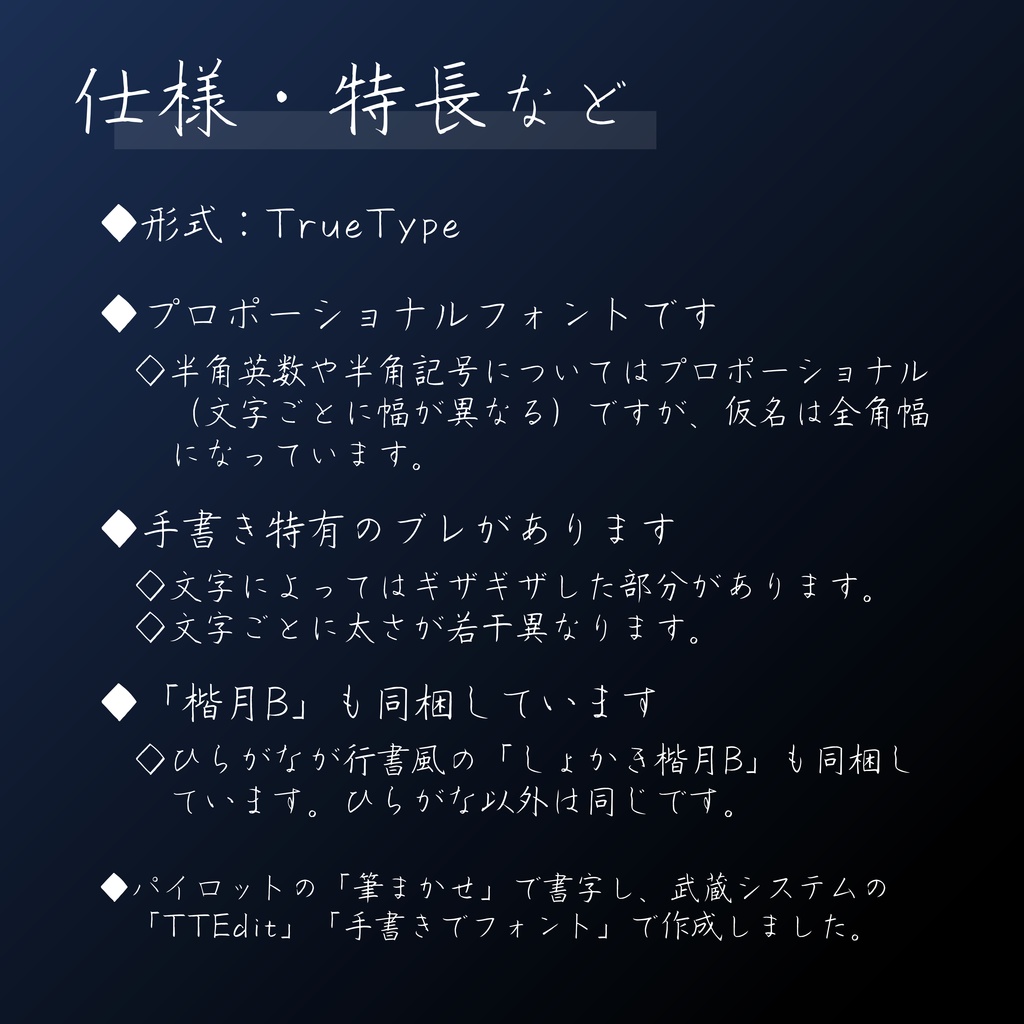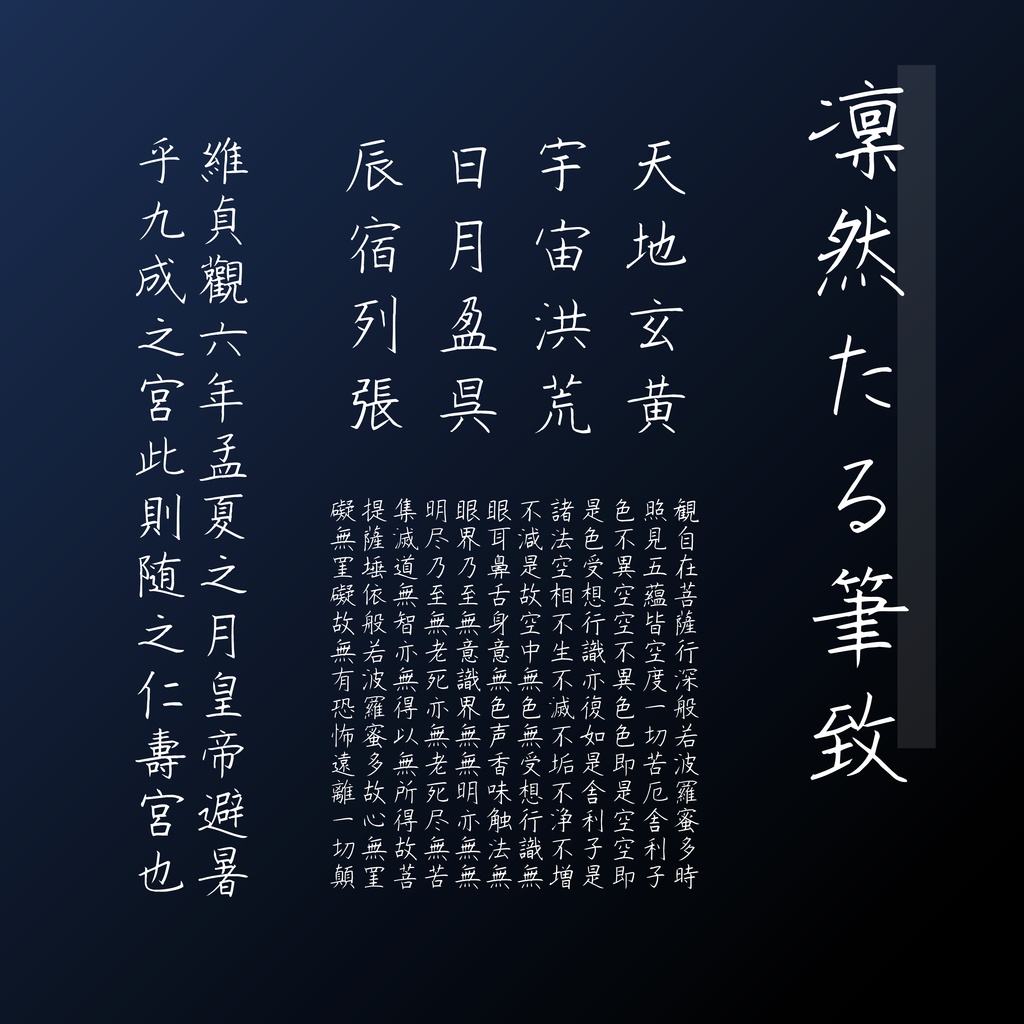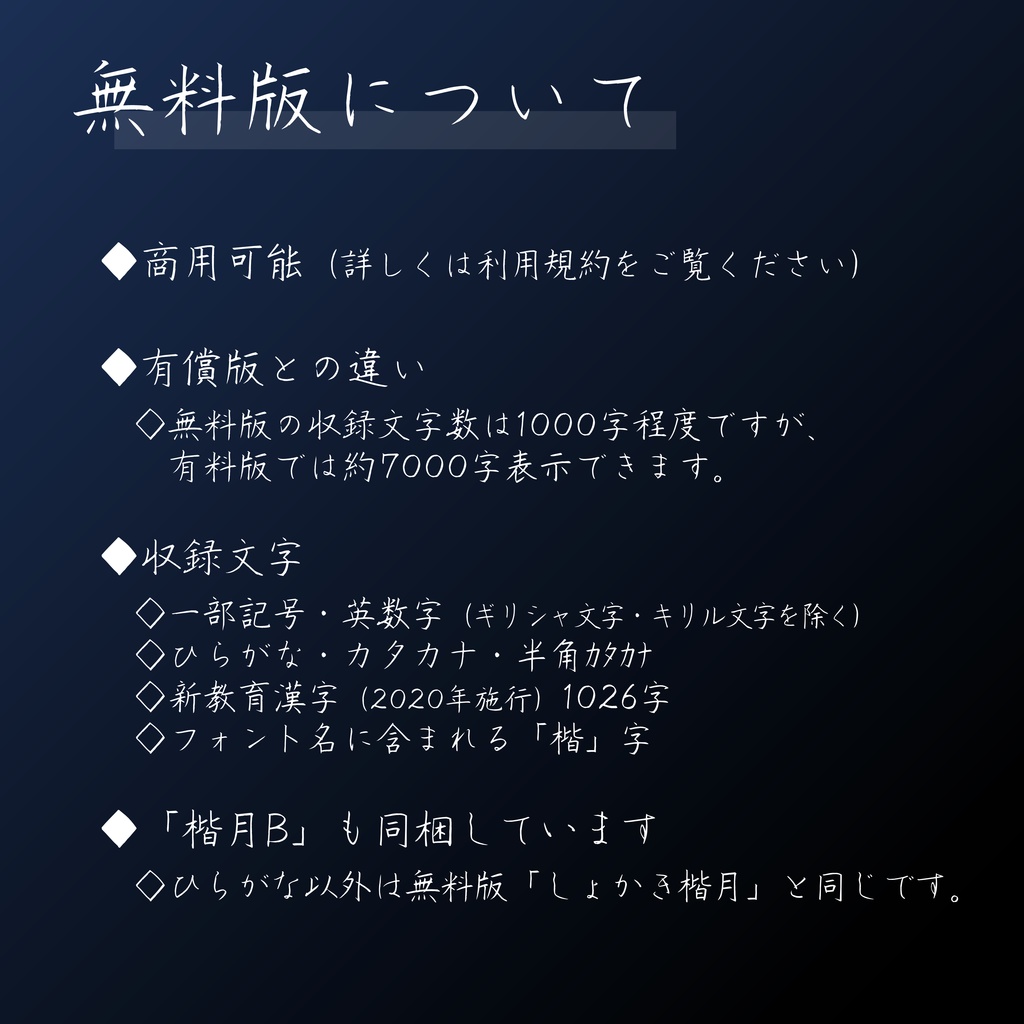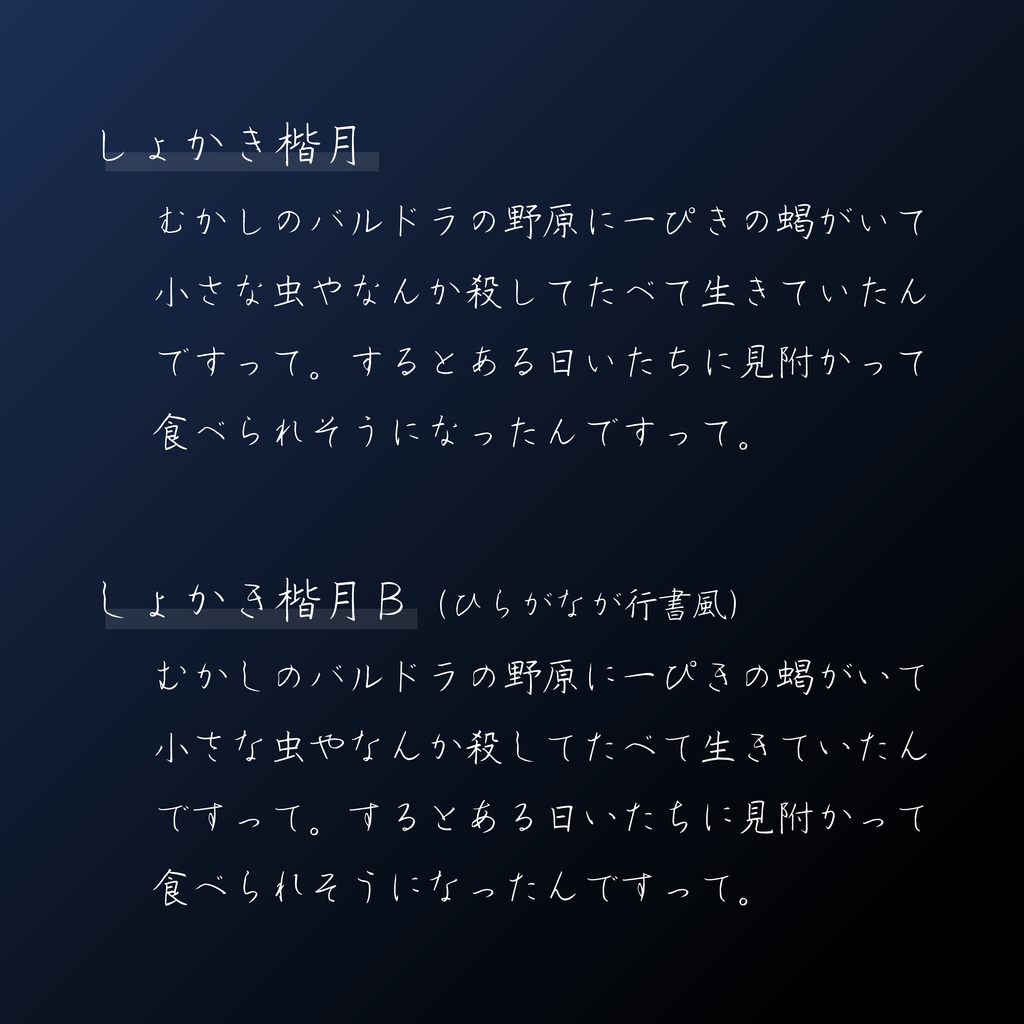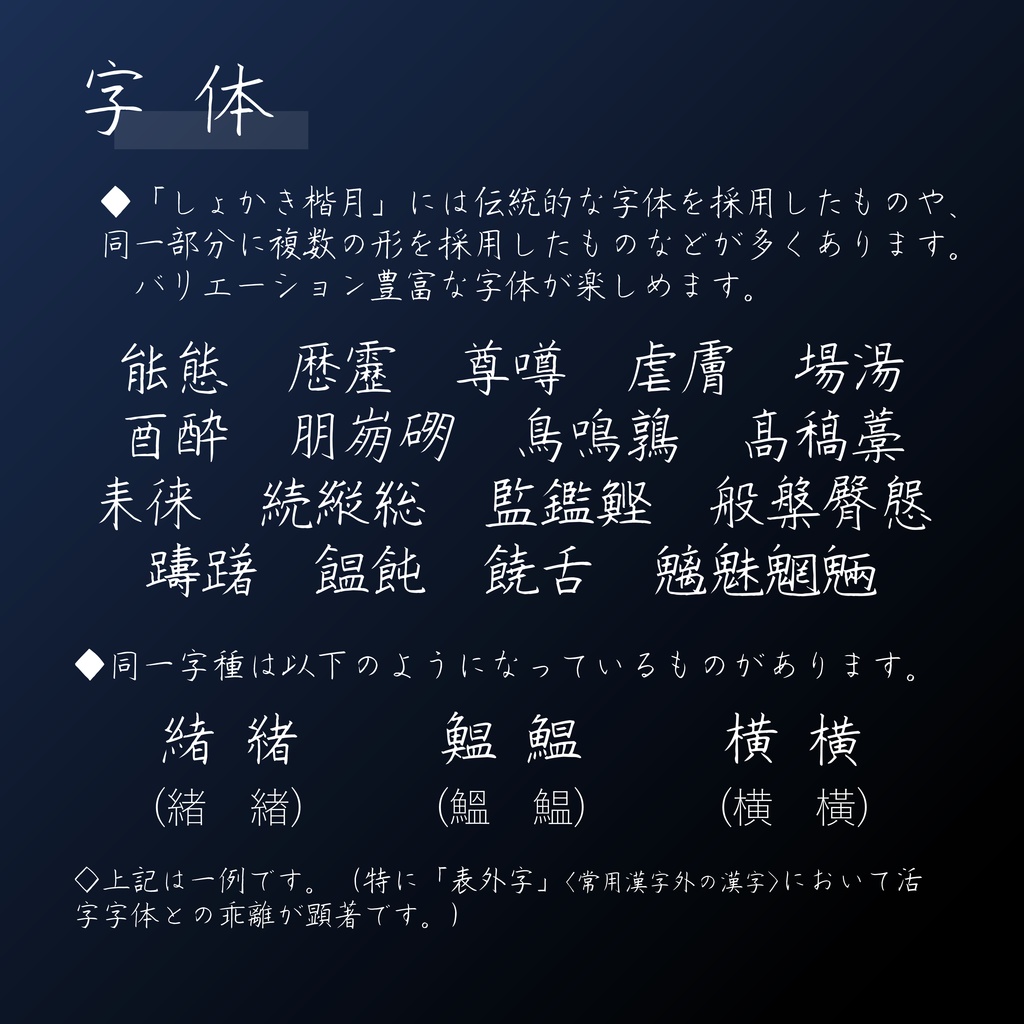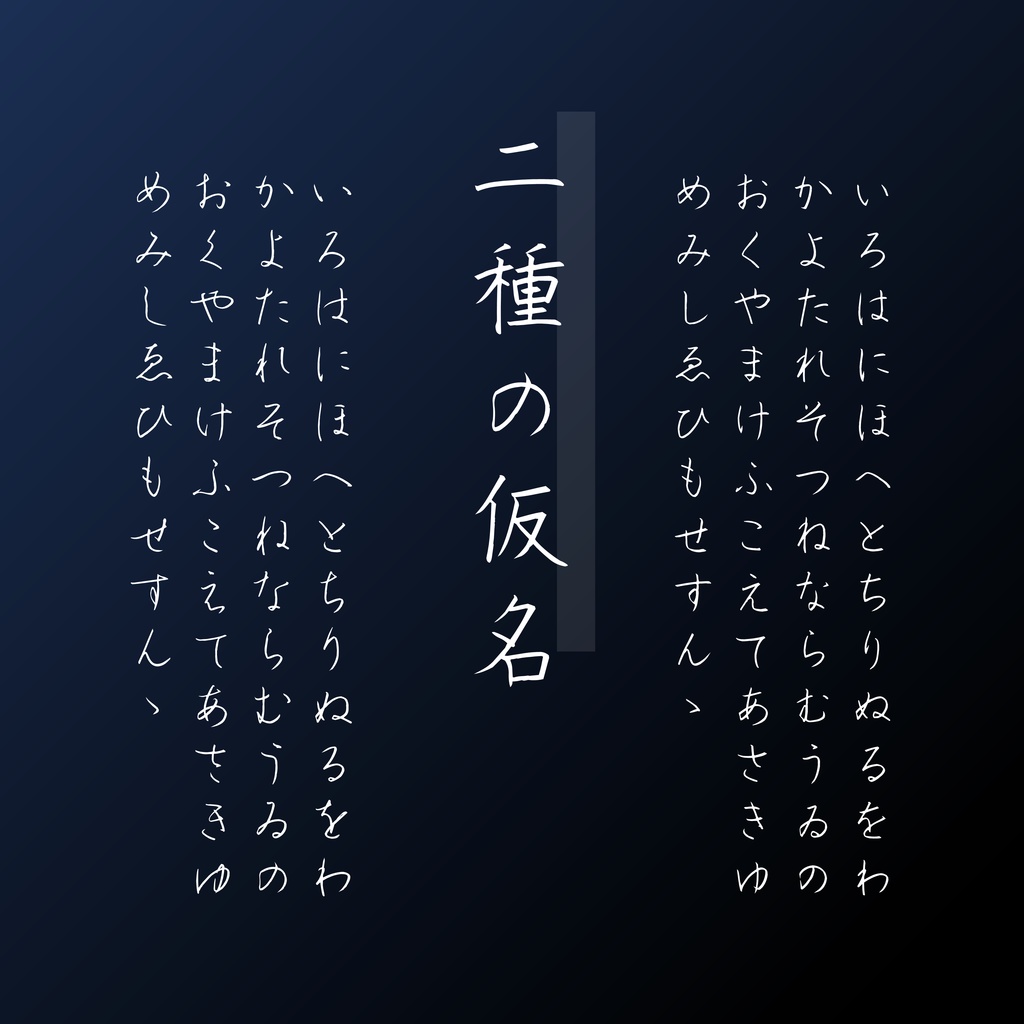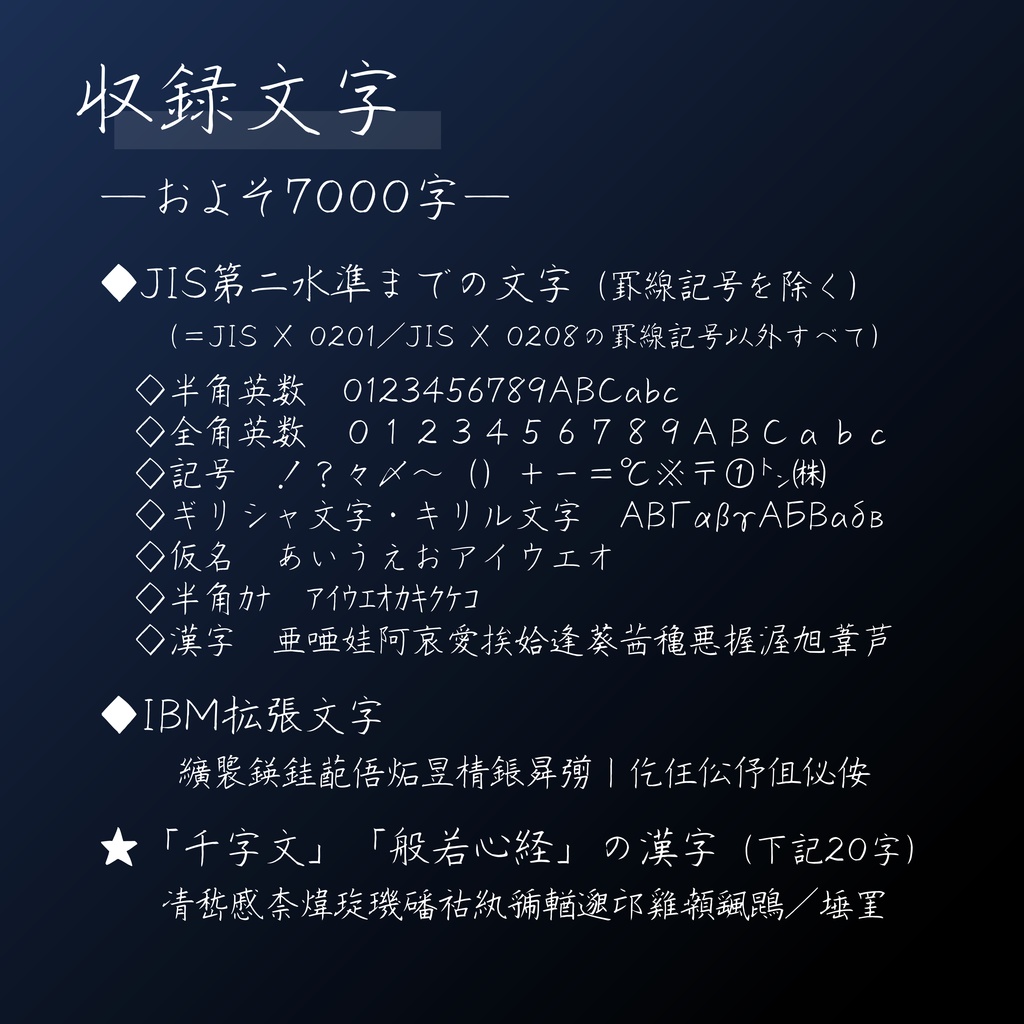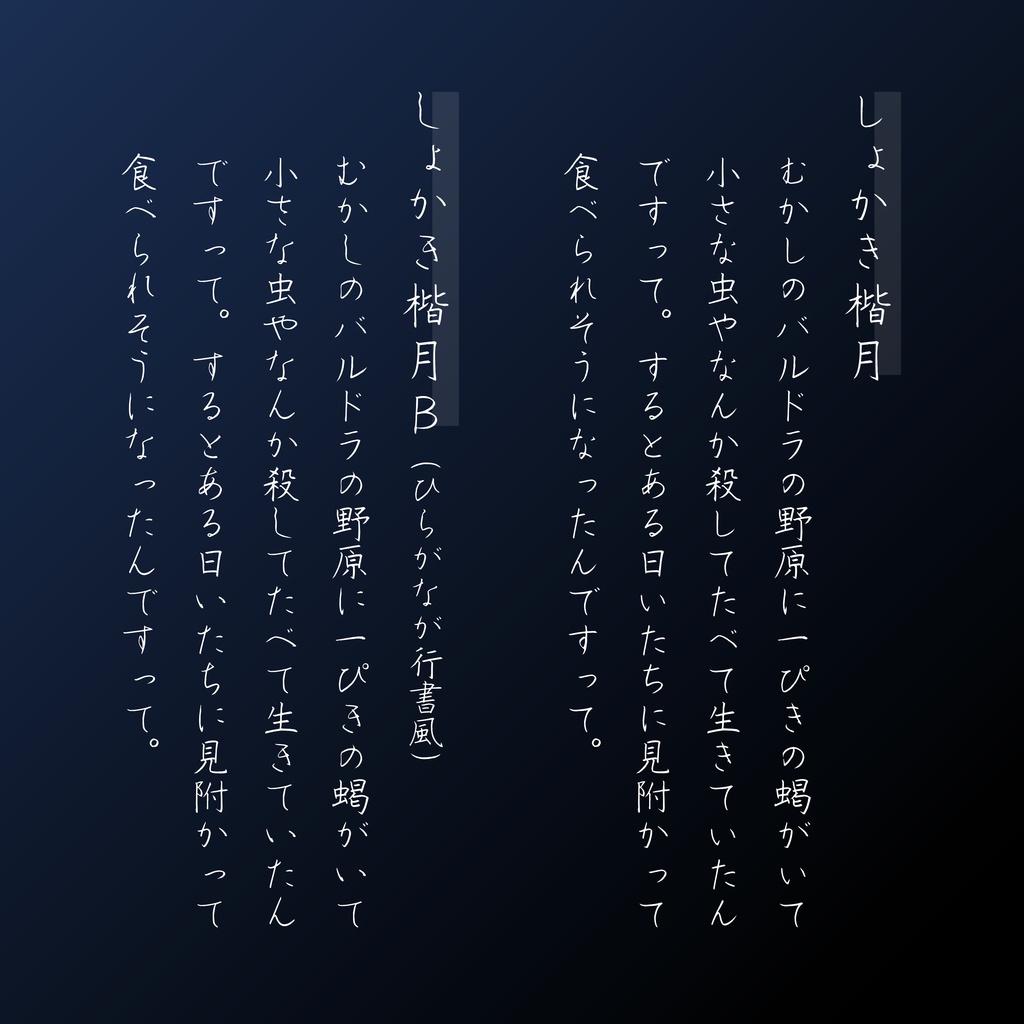
しょかき楷月【フリーフォント版あり】
◆おしらせ◆ 2024年10月24日 利用規約を改定し、しょかきのフォント統一の使用許諾契約となりました。 新作フォントできました。 https://shokaki.booth.pm/items/4097318 【ペン字楷書フォント「しょかき楷月」について】 ◆特徴など◆ ・凛々しい楷書を目指して書いたフォントです。 ・すべて手書きの字を元に作られています。 ・異体字などで書かれている漢字があります。(無料版に通常版の文字一覧の画像を同梱しています) ・月のように凛々しい楷書ということで、「楷月(かいげつ)」と命名しました。 ・フォントの作成についての解説記事も書きましたので、ぜひお読みください。 https://shokaki.hatenablog.jp/entry/2022/04/28/164107 ・標準字体版も作成予定ですが、完成は未定です。 ・有計劃做一套繁體字(Big5-1984)版本字體。/繁体字(Big5-1984)版を作ることも計画しています。 ◆基本情報◆ ・形式:TrueType ・プロポーショナルフォントです。(半角英数や半角記号についてはプロポーショナルですが、仮名は全角幅になっています。) ・パイロットの「筆まかせ」というペンを使って書きました。 ・本ファイルは武蔵システム(https://opentype.jp/)の「TTEdit」「手書きでフォント」を使って作成しました。 ・技術提供:kurgm氏 https://github.com/kurgm/addglyph/releases ◆バージョンについて◆ 「しょかき楷月」 「しょかき楷月B」 上記2つのバージョンと、その無料版があります。 「楷月B」は平仮名の書き方が行書風です。他の文字は同じです(同梱しています)。 無料版は無料で使用できますが、収録文字が少ないものです。 利用規約(使用許諾)は同じです(下記)。
【「しょかき楷月/楷月B」(通常版)について】 ◆基本情報 ・形式:TrueType ・プロポーショナルフォント ・「楷月B」はひらがなのみが異なります。 ◆収録文字 ・JIS第二水準までの文字(罫線記号を除く)(=JIS X 0201/JIS X 0208の罫線記号以外すべて) ・IBM拡張文字 ・追加で「千字文」「般若心経」の漢字(凊嵆慼柰煒琁璣磻祜紈虢輶邈邙雞顙颻鵾/埵罣)を収めています。 【「しょかき楷月/楷月B(無料版)」について】 無料版は無料で使用できます。 ◆収録文字 一部記号・英数字・仮名・新教育漢字を収録しています。 ギリシャ文字・キリル文字などは表示できません。 また、フォント名の「楷」も収録しています。 通常版の文字一覧画像も同梱していますので、ご購入の際の文字の確認にお使いください。 ◆有償版との違い 収録文字数が圧倒的に異なります。 教育漢字は1026字ですが、JIS第二水準漢字までですと、およそ6000字が表示できます。